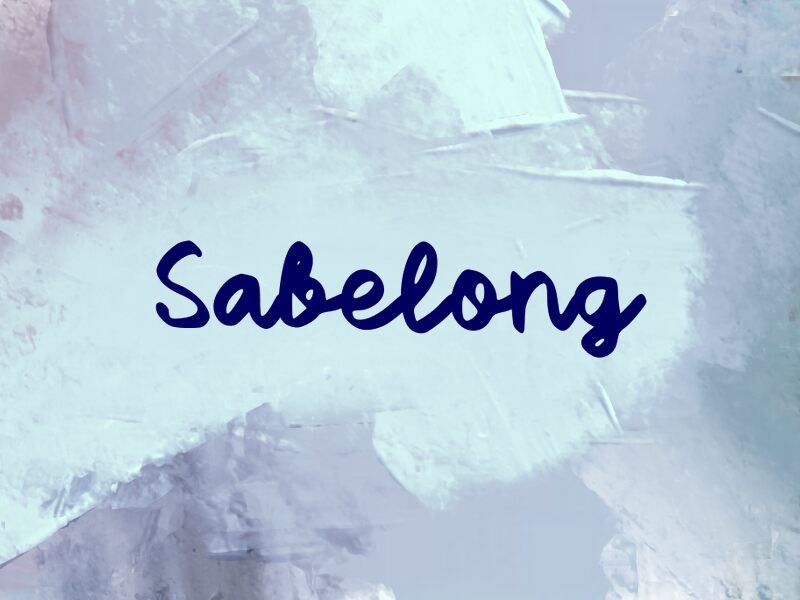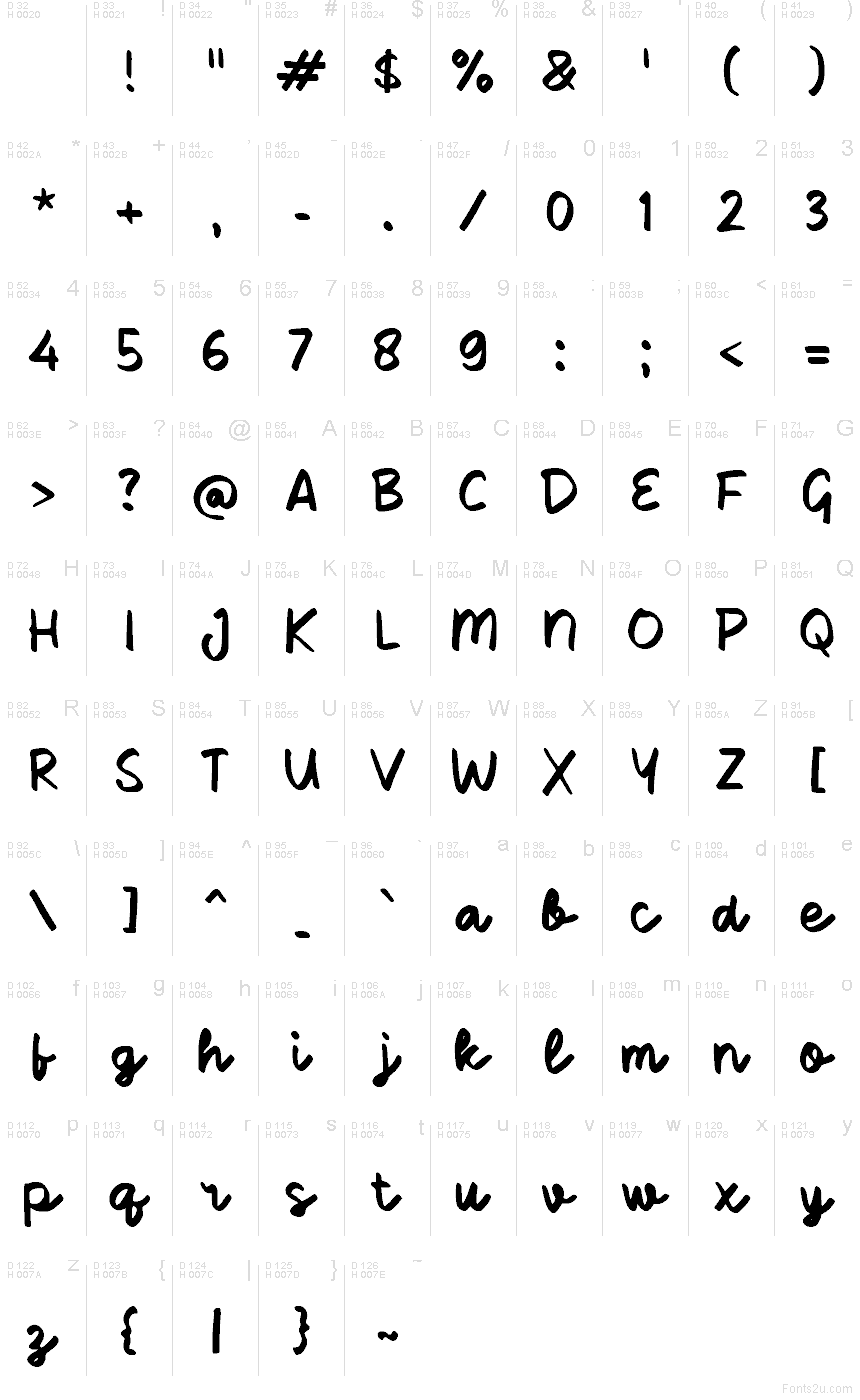
Sabelong
Sabelong by Wep 是一款免费的手写字体,由宽阔圆润的笔触和从左向右的自然流畅感塑造而成,比起正式的书法字,它更像是一种马克笔书写的质感。字体节奏松散且连贯,圆润的曲线与不规则的笔画连接,赋予了这款字体休闲随性的手写流向,而非那种过于雕琢的艺术感。
这种轻松的动态非常适合咖啡馆品牌设计、产品包装、社交媒体图片、邀请函标题以及引言艺术,能在设计中传递出个人化和即时的亲切感。对于短标题和标志类文本来说,如果想要这种友好、签名式的笔触,同时又想避免传统连体字那些繁琐的细节,这款字体将是极佳的选择。